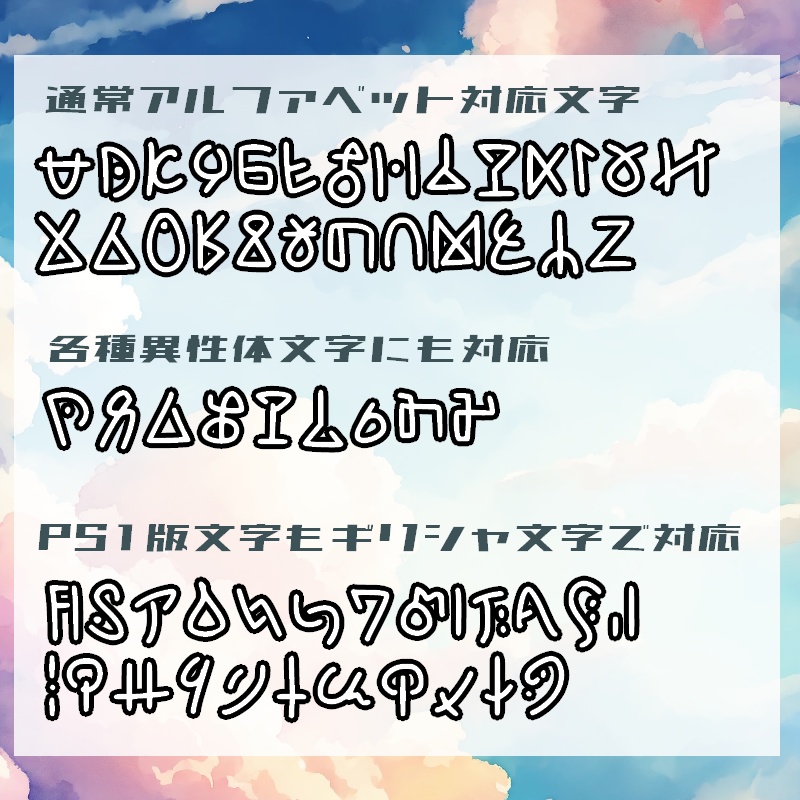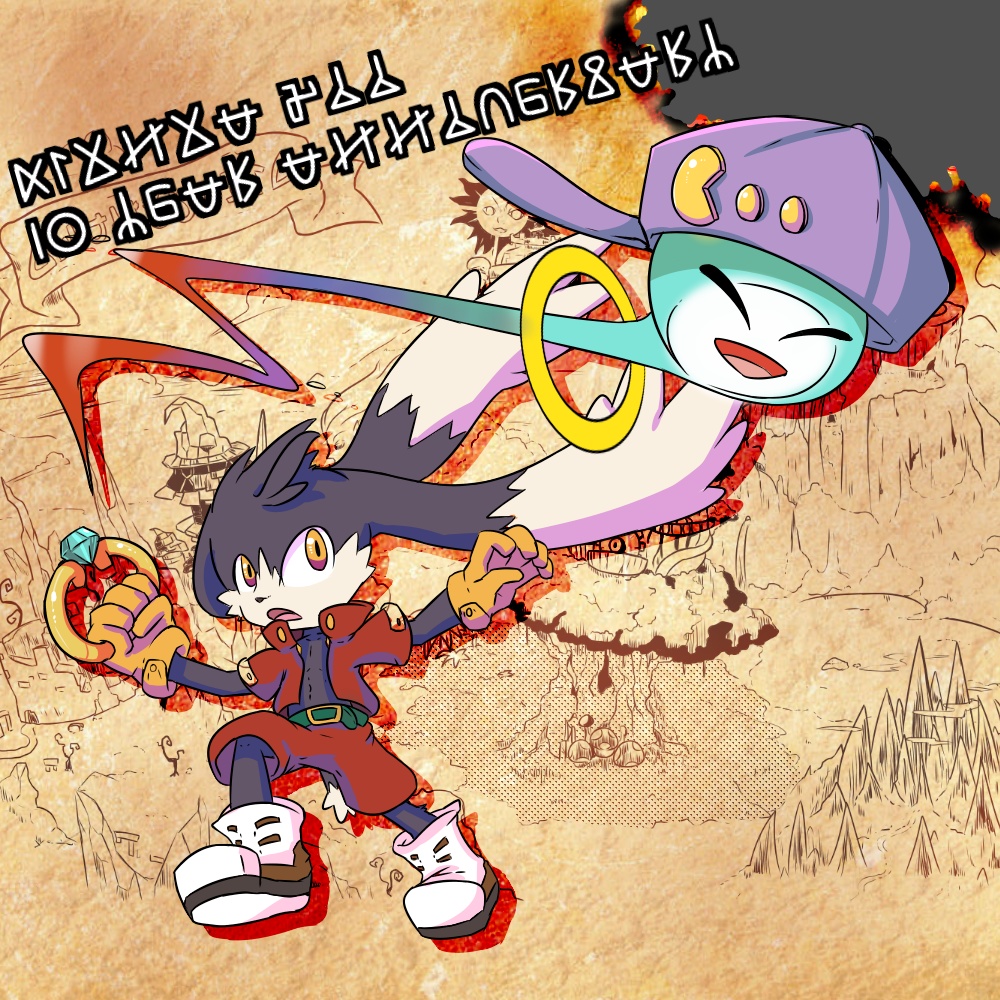
Phantomaile Art Font
『Phantomaile Art Font』は風のクロノア door of Phantomileに登場する架空文字を可能な限り解読し設計したフォントです. クロノア作品での創作活動などにお役立ていただけると幸いです. このフォントファイルにはPS版風のクロノアおよび,Wiiリメイク版で使用された文字が含まれています. 対応文字や細かい仕様については同封のreadmeテキストを参照してください. =========================================== このフォントはデザイン用途にご使用いただけます. 【利用規約】 ・印刷物,映像作品,グッズ作成等での利用はOK ・ロゴマーク等への画像への加工使用もOK ・スクリーンショット/撮影/公開はOK ・改変/再配布/自作発言はNGです 利用報告は必須ではありませんが,報告してくれると作者が喜びます.